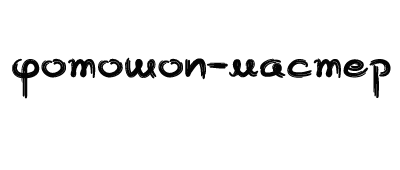
Шрифт - Burlak
Интересный шрифт, который хорошо подходит для работы в фотошопе. Есть поддержка русского языка.
Внешний вид:
Хех, исключительно на русском, такая красота??? прям нет слов! Спасиб))))
шрифт офигенный, а кто может подскажет аналог чтобы и английскими буквами можно было писать?